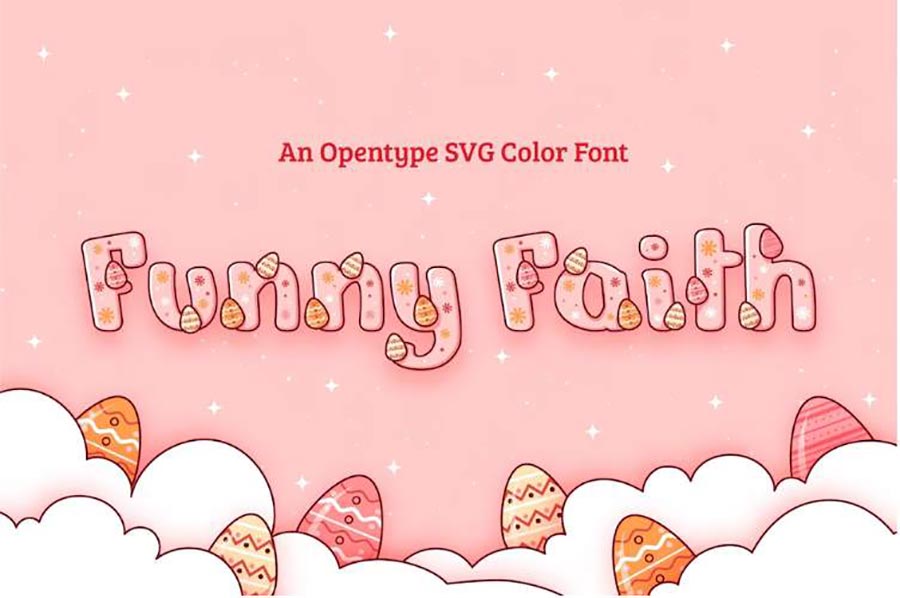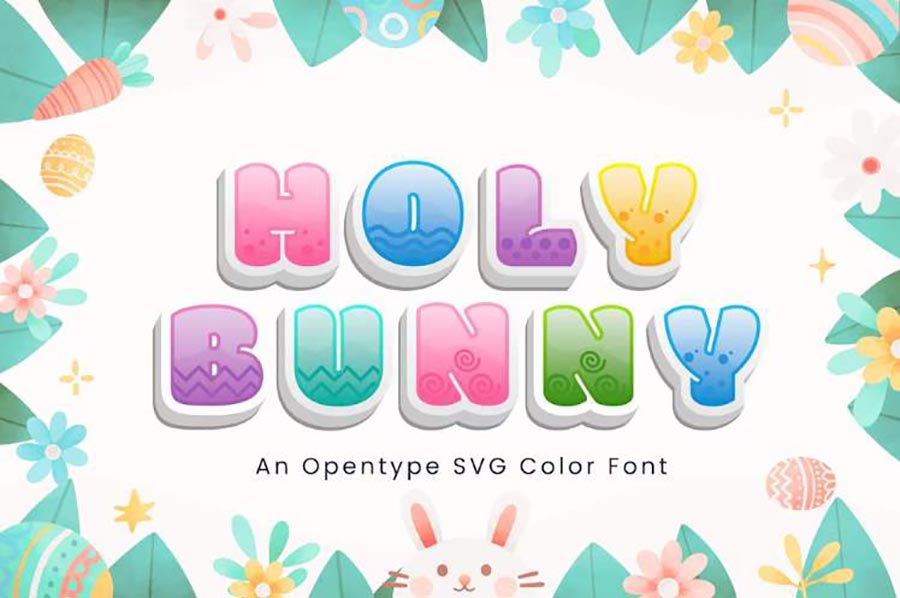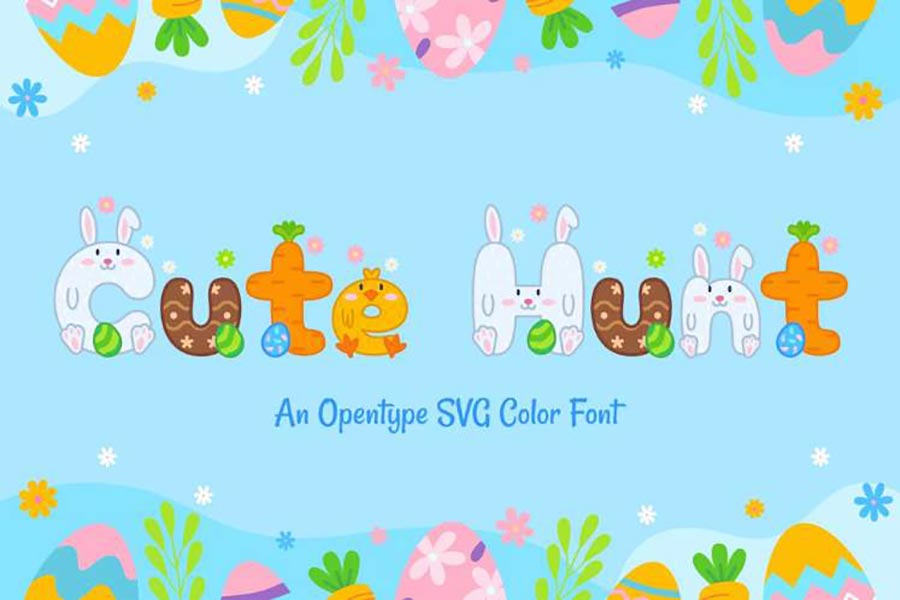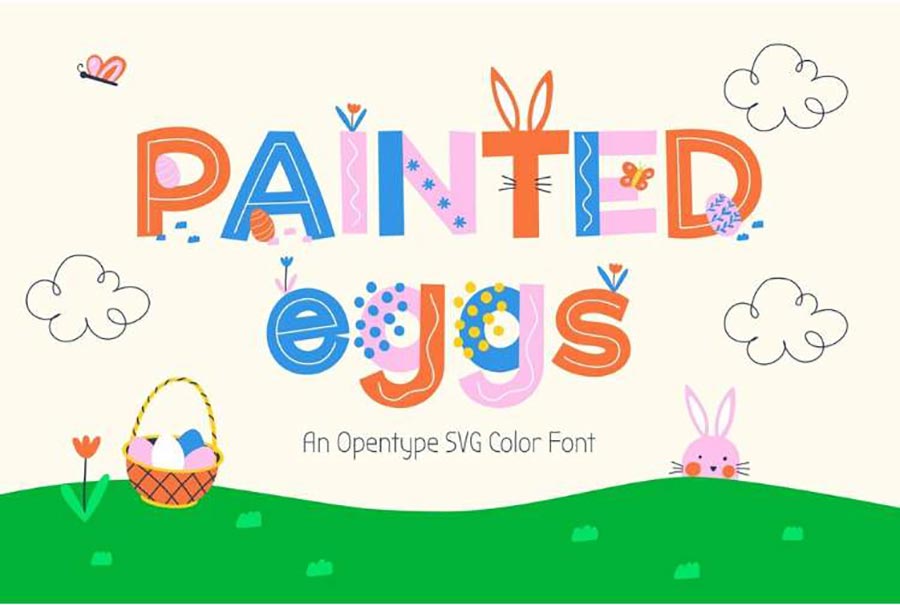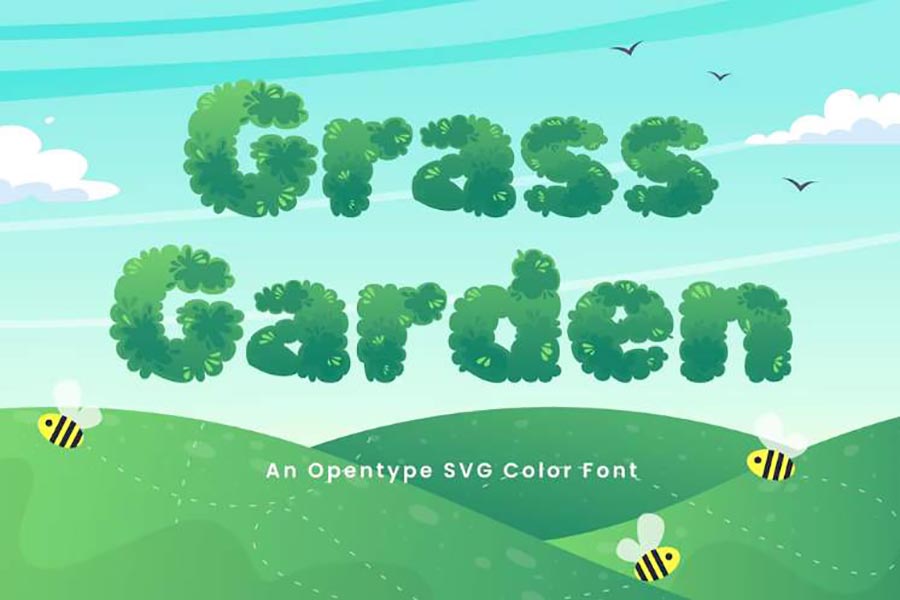
Chia Sẻ Miễn Phí Tải Bộ Fonts Easter Cực Đẹp
Khi thiết kế đồ họa, lựa chọn font chữ không chỉ ảnh hưởng đến tính thẩm mỹ mà còn quyết định hiệu quả truyền tải thông điệp. Nếu bạn đang tìm kiếm những kiểu chữ đặc biệt và ấn tượng cho các dự án thiết kế mùa lễ hội, bộ font "Easter" miễn phí từ Sadesign.vn chính là sự lựa chọn tuyệt vời. Với những font chữ dễ thương, vui tươi, bộ sưu tập này sẽ giúp bạn tạo ra các thiết kế bắt mắt, phù hợp với không khí lễ hội Phục Sinh. Hãy cùng khám phá bộ fonts Easter cực đẹp này ngay trong bài viết dưới đây.
Bộ Fonts Easter Miễn Phí Là Gì?
Bộ fonts "Easter" là một bộ sưu tập những kiểu chữ thiết kế đặc biệt, được lấy cảm hứng từ không khí vui tươi, sắc màu của mùa lễ hội Phục Sinh. Những font chữ này mang trong mình sự nhẹ nhàng, thanh thoát, thường đi kèm với các chi tiết dễ thương như hình ảnh trứng Phục Sinh, những đóa hoa pastel, hay hình ảnh những chú thỏ ngộ nghĩnh. Bộ font Easter này sẽ là công cụ lý tưởng để bạn tạo ra những thiết kế vừa độc đáo, vừa bắt mắt.
2. Tính Sáng Tạo Cao: Những kiểu chữ trong bộ này được thiết kế đặc biệt để tạo điểm nhấn trong các dự án của bạn.
4. Dành Cho Mọi Dự Án: Cho dù là thiết kế thiệp mời, quảng cáo, bài viết blog hay các sản phẩm sáng tạo khác, bộ fonts Easter đều rất phù hợp.
Ứng Dụng Bộ Fonts Easter Trong Thiết Kế:
Bộ fonts Easter không chỉ đẹp mà còn rất linh hoạt trong ứng dụng. Dưới đây là một số gợi ý về cách bạn có thể sử dụng bộ font này:
1. Thiết Kế Thiệp Mời Lễ Hội: Bộ fonts Easter là lựa chọn hoàn hảo để thiết kế thiệp mời cho các sự kiện lễ hội, đặc biệt là dịp Phục Sinh.
2. Thiết Kế Quảng Cáo Mùa Lễ: Sử dụng bộ fonts này để tạo ra các banner, poster quảng cáo hoặc chiến dịch email marketing mùa lễ hội Phục Sinh.
3. Sáng Tạo Nội Dung Mạng Xã Hội: Chia sẻ những câu chúc mừng lễ hội trên Instagram, Facebook với bộ fonts độc đáo, thu hút sự chú ý của người xem.
4. Thiết Kế Sản Phẩm In Ấn: Những bộ fonts dễ thương này cũng có thể được dùng cho các ấn phẩm in ấn như sách ảnh, túi quà, áo phông, hay sản phẩm quà tặng.